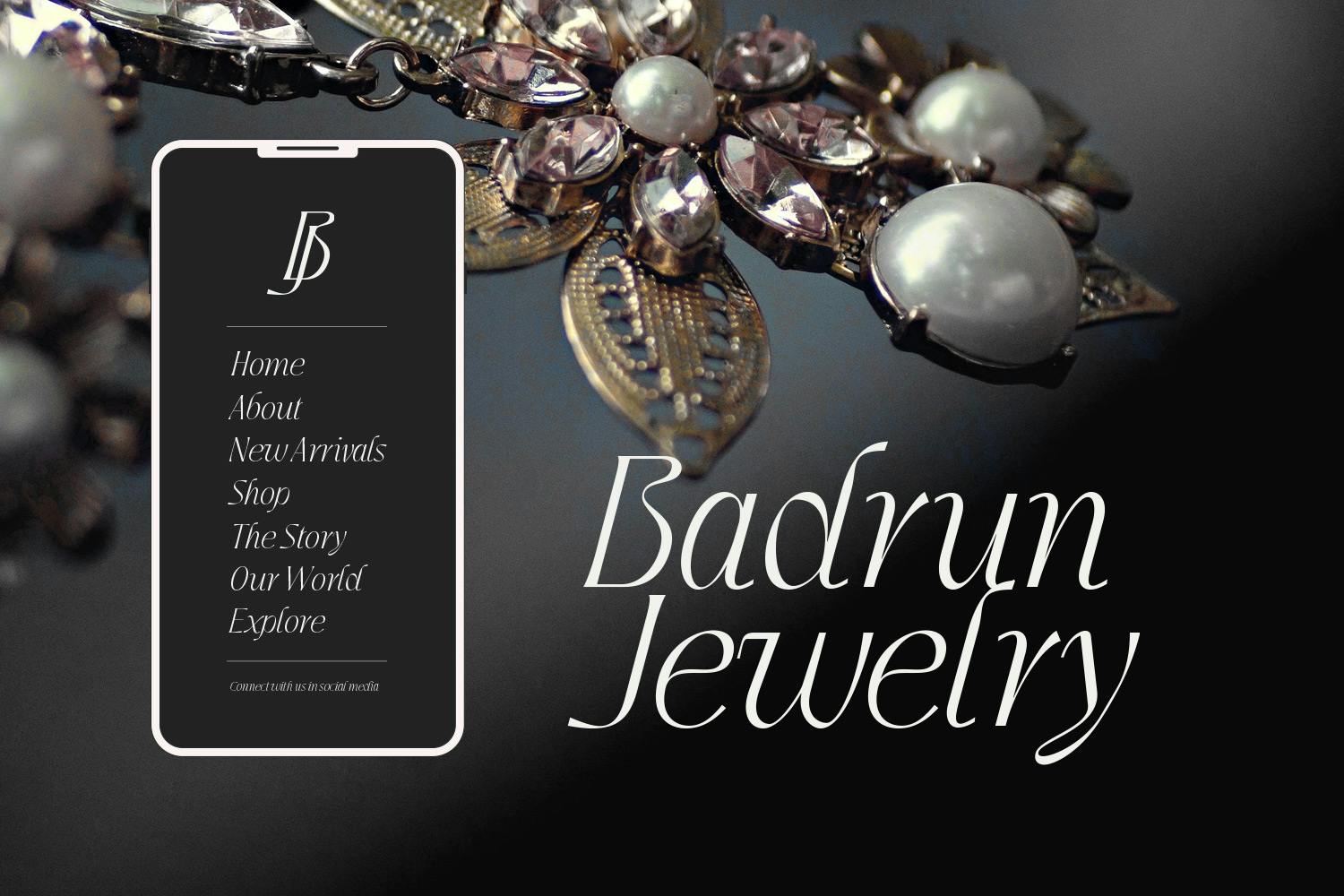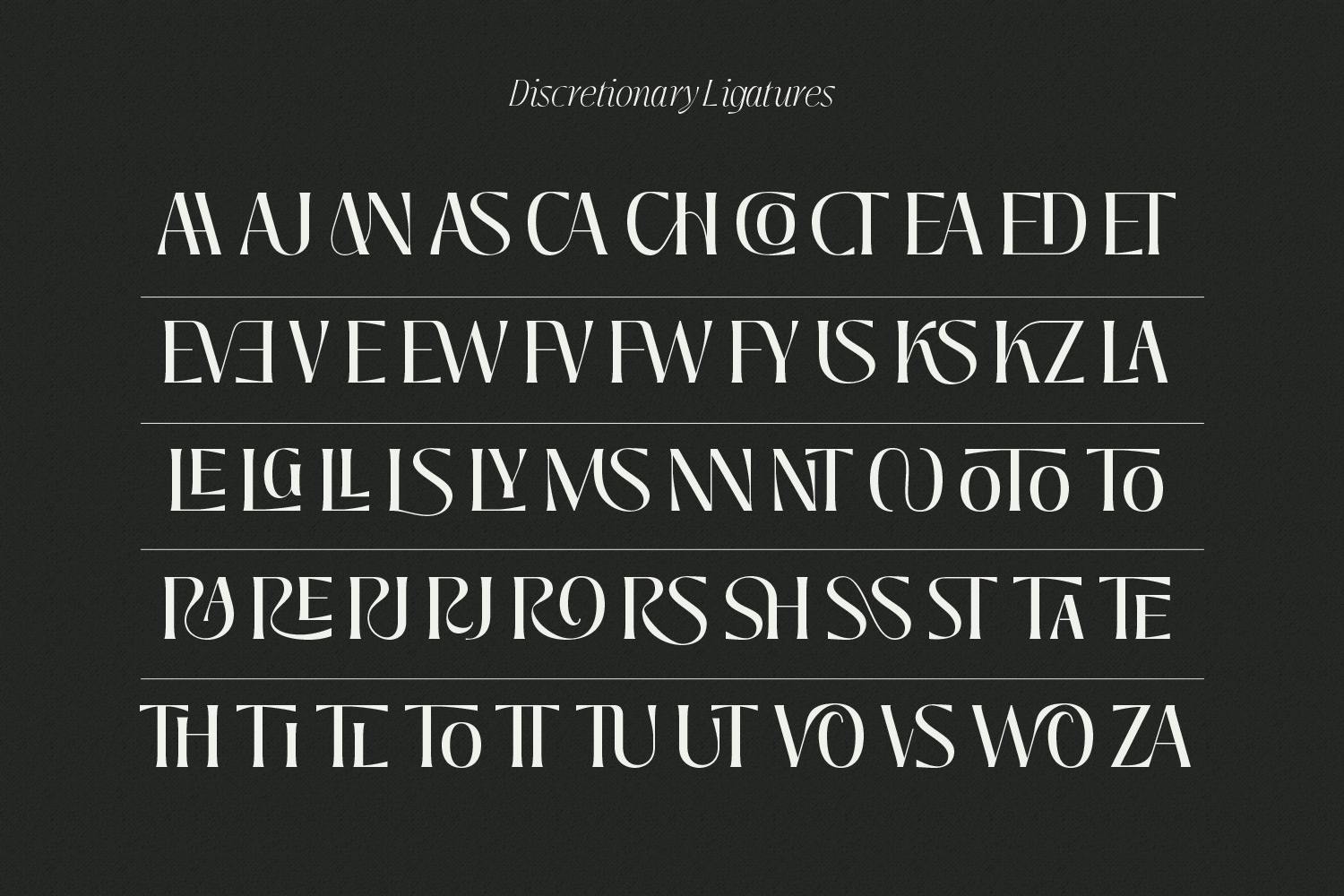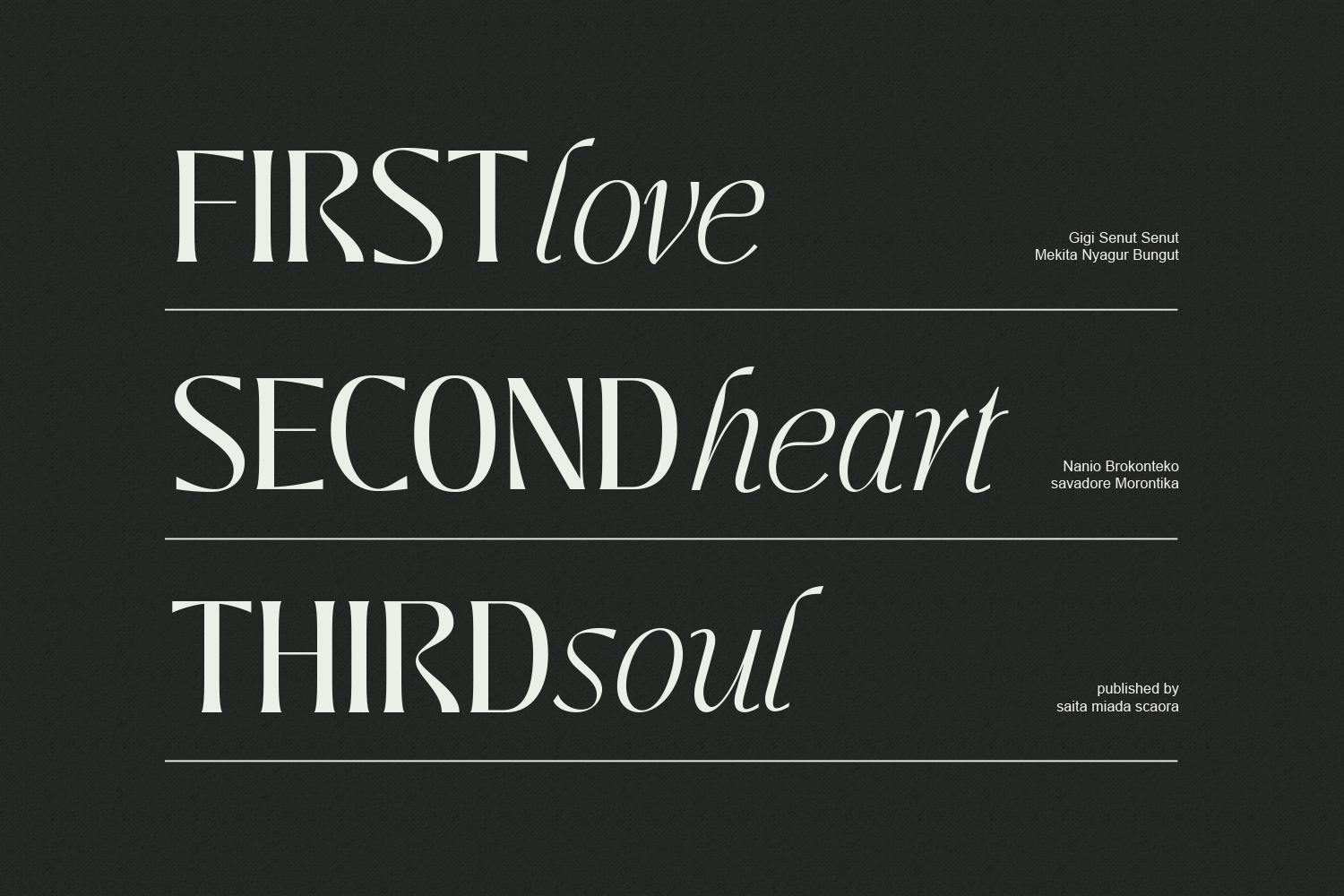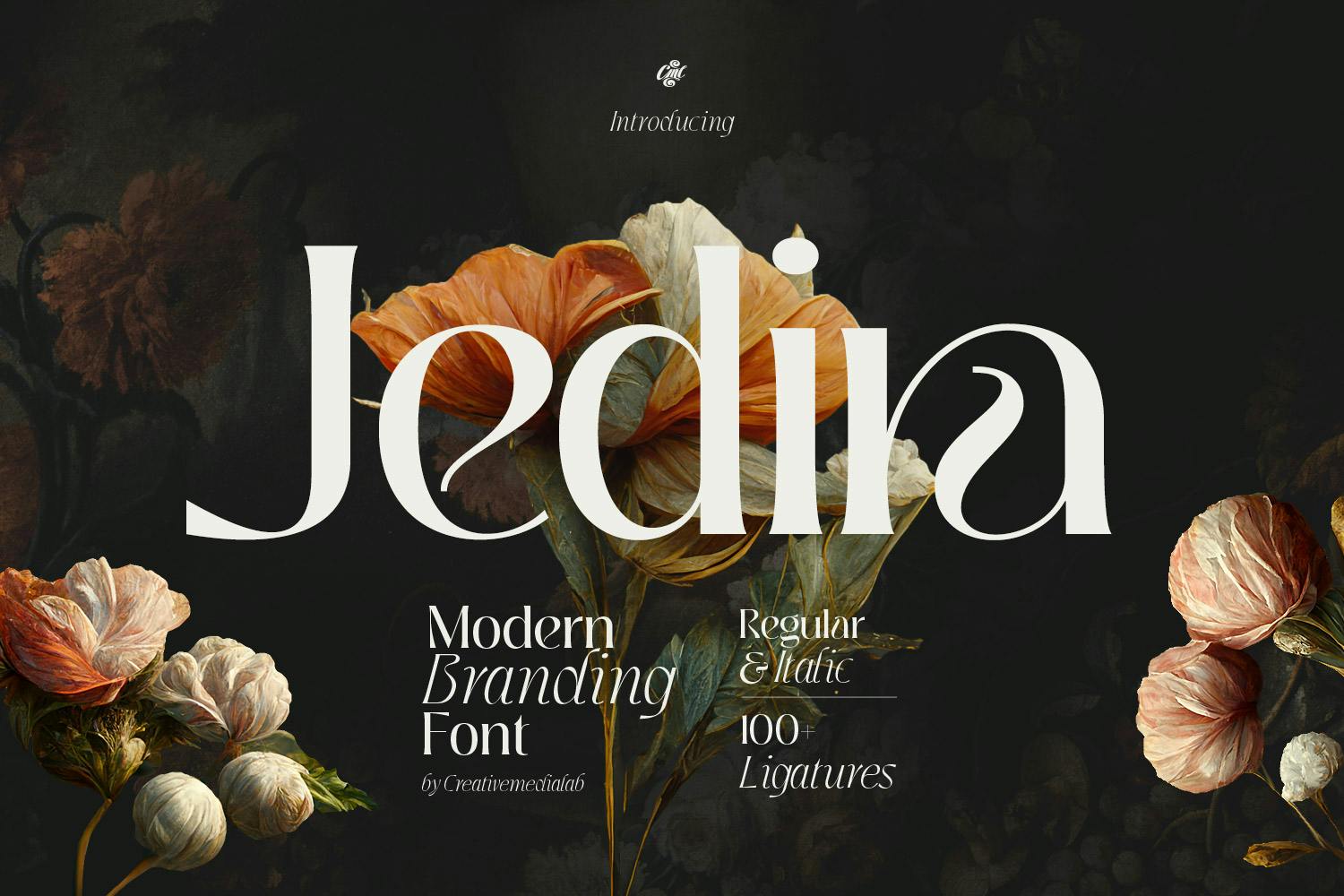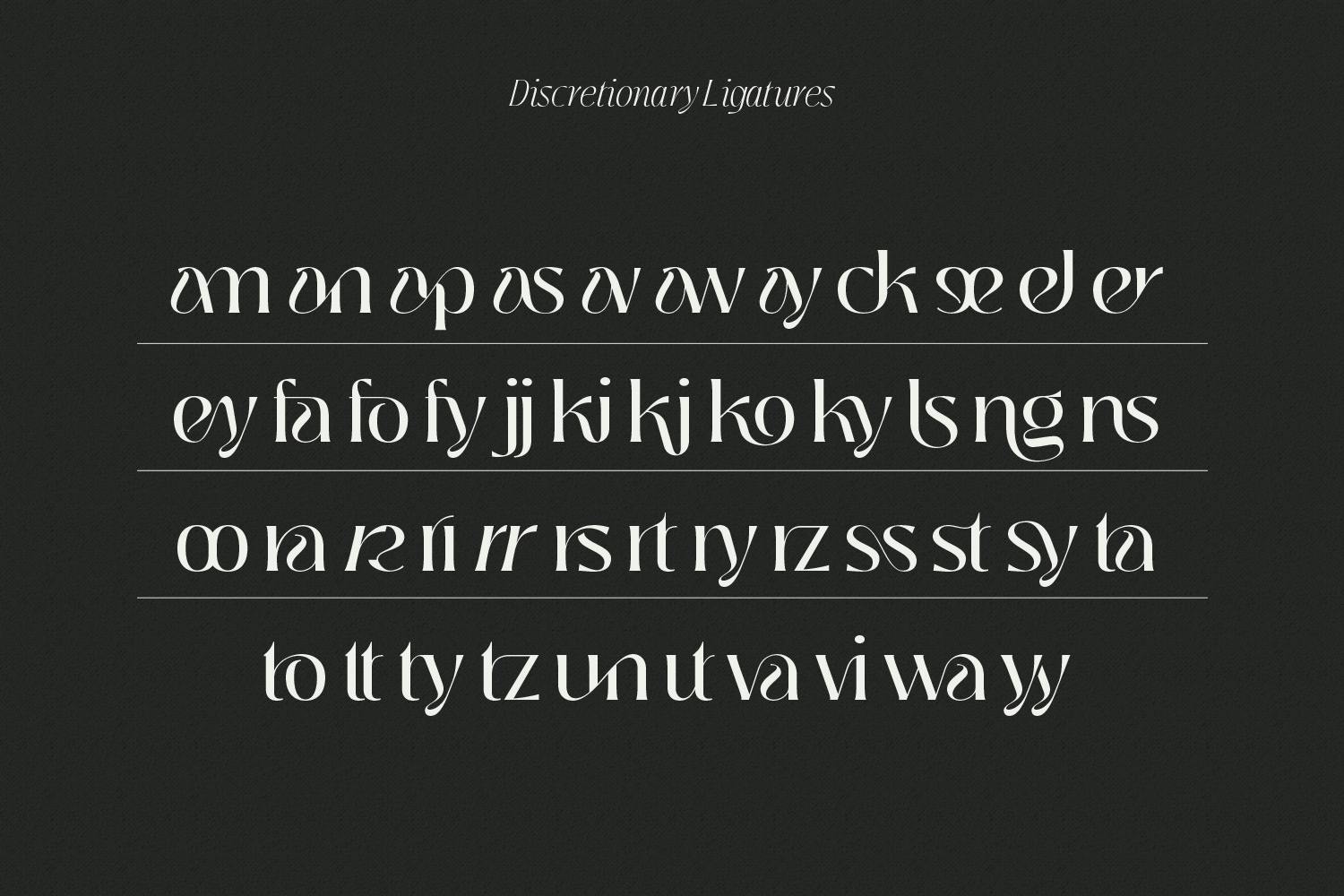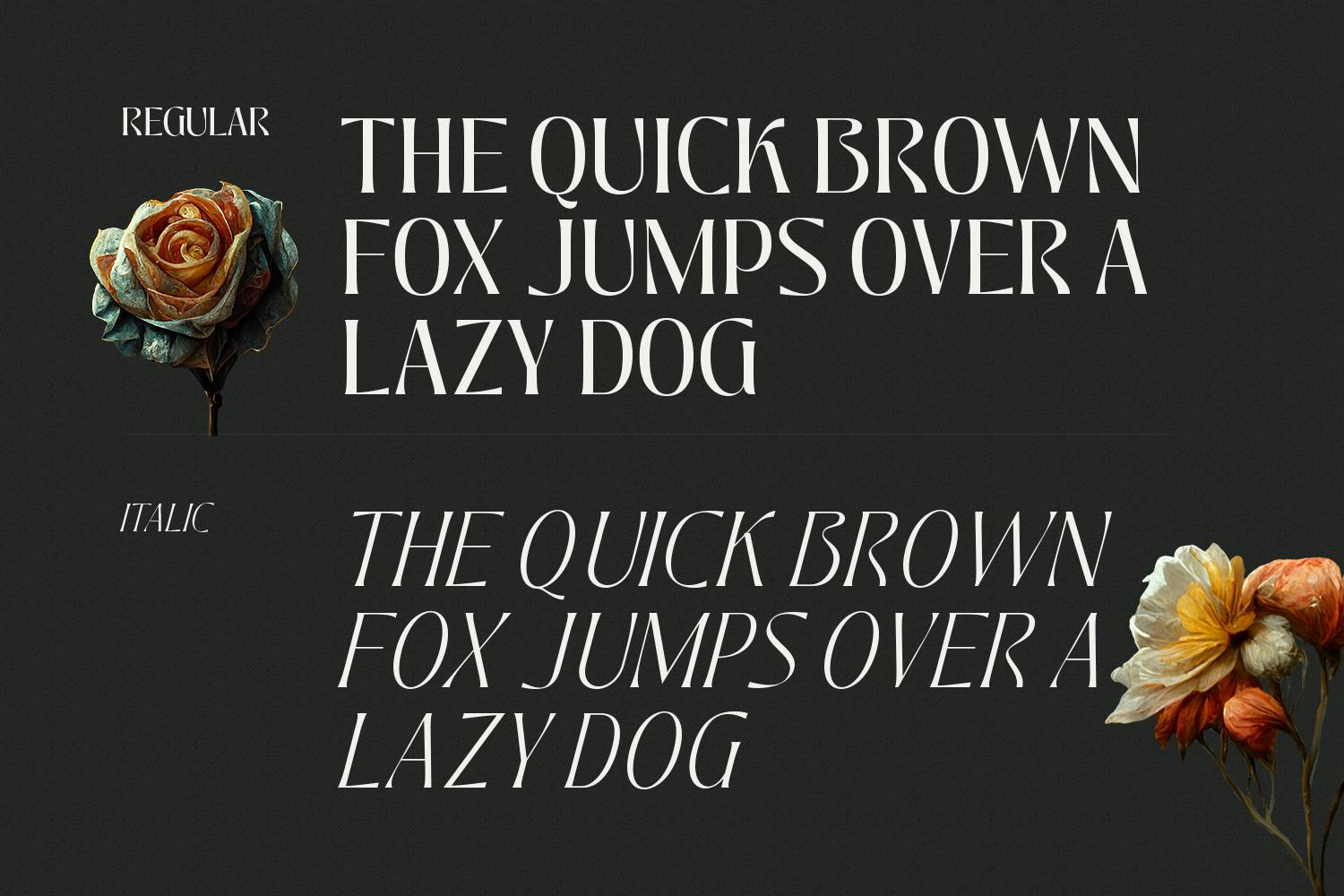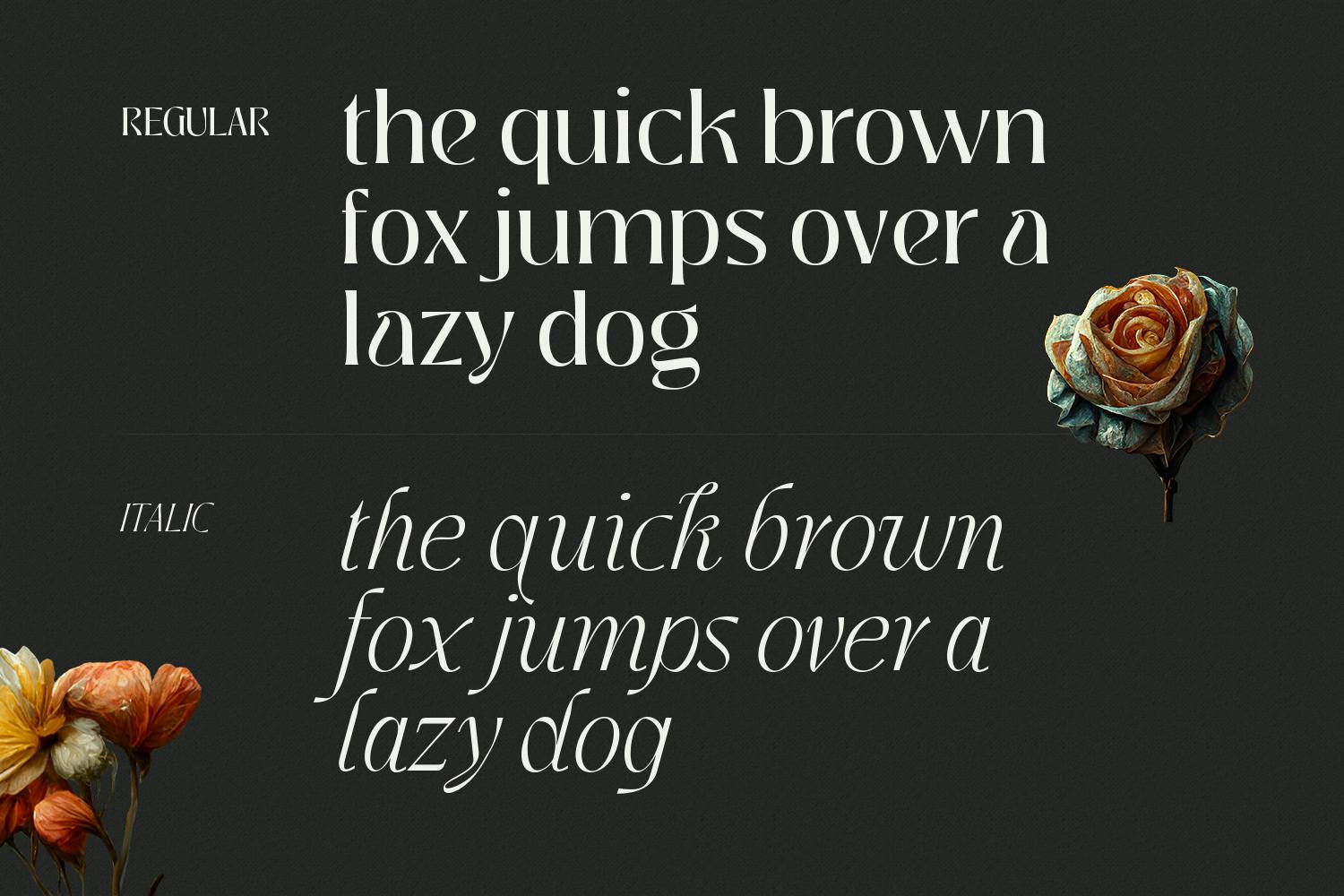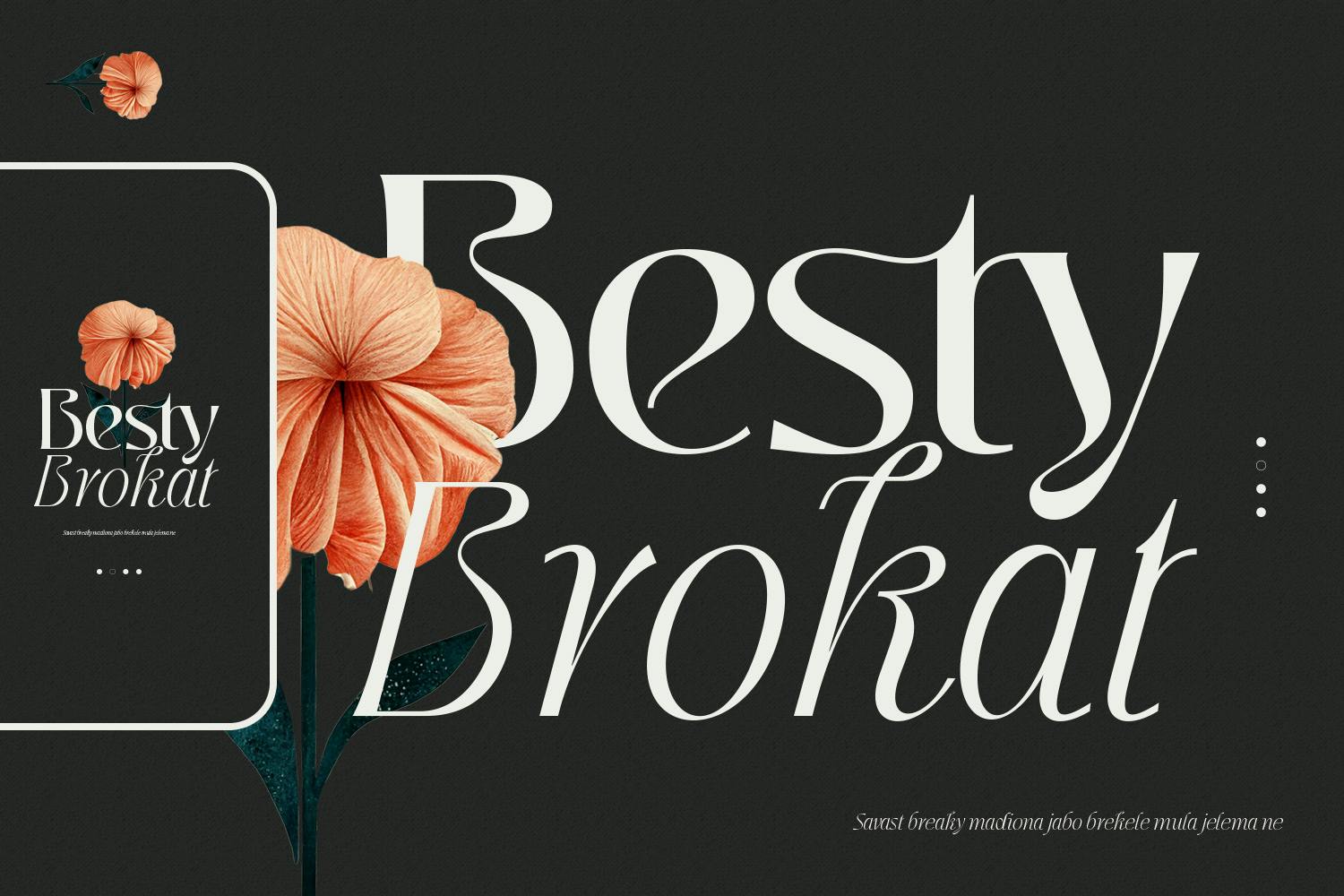
دانلود فونت لوگوی مدرن جدیرا
Jedira Modern Branding Logo font
فونت جدیرا با طراحی شیک و کلاسیک، مناسب برای پروژه‌های برندینگ.
فونت جدیرا یک فونت نمایشی شیک و کلاسیک است که دارای ایتالیک هماهنگ و تعداد زیادی لیگاتور می‌باشد. این فونت چندمنظوره برای برندینگ، طراحی وب، لوگو، مفاهیم مرتبط با مد و بسیاری از پروژه‌های دیگر مناسب است.
• طراحی مدرن و زیبا
• دارای ایتالیک هماهنگ
• مناسب برای پروژه‌های برندینگ و وب
• شامل لیگاتورهای متنوع